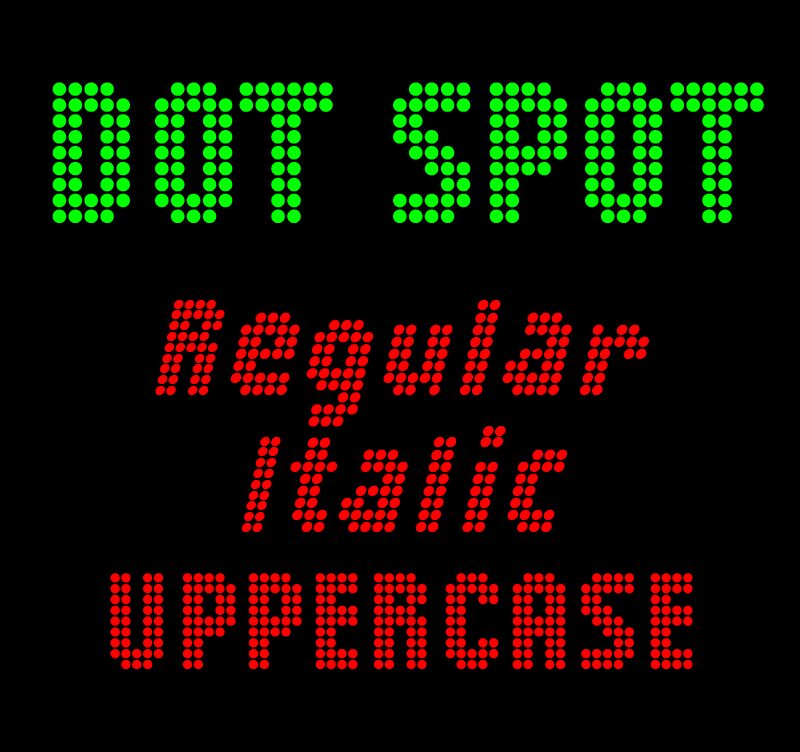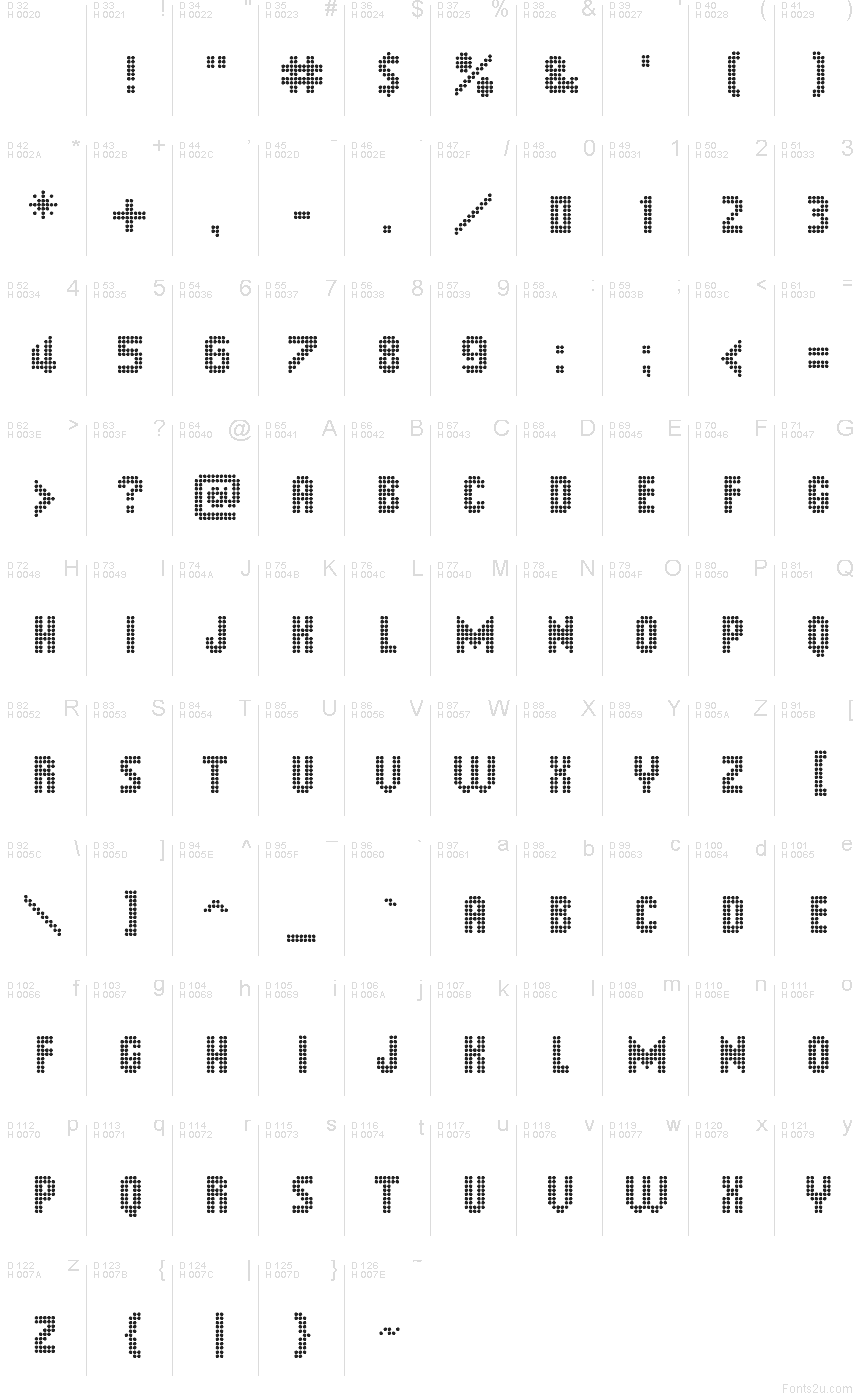
Dot Spot UC, de Galdino Otten, es una tipografía display gratuita de puntos con un aire a letrero luminoso. Las mayúsculas están construidas con puntos circulares uniformes, haciendo que las letras se vean como un cartel retro o un marcador electrónico, donde la geometría simple hace todo el trabajo.
Funciona ideal para pósteres, flyers de eventos, gráficos musicales, branding retro tecnológico, tarjetas de título y líneas de texto cortas donde la cuadrícula de puntos marca el estilo. Al ser gratuita, también es perfecta para monogramas e iniciales de logos, ya que su patrón repetitivo aporta una textura rítmica y dinámica incluso a las palabras más sencillas.